나의 활자 디자인 철학, 마르틴 마요르 Martin Majoor_후편
스칼라와 스칼라 산스. 두 개의 활자체, 하나의 형태원칙
나는 1987년에 스칼라를 디자인하기 시작했다. 당시 나는 위트레흐트에 소재한 프레던뷔르흐 음악센터에 소속된 두 명의 그래픽 디자이너 중 하나였다. 이곳은 네덜란드의 다른 어떤 연주회장보다 많은 공연들이 기획된 대형 콘서트 홀이었다. 우리는 애플 맥킨토시의 첫 모델로 작업했고, 페이지 메이커 1.0을 사용했는데, 여기서 골라쓸 수 있는 활자체는 16가지가 전부였다. 나는 올드 스타일 피겨(osf, old style figure)라고도 불리는 소문자형 숫자(lowercase number), 작은 대문자(small cap), 이음글자(ligature)를 사용하도록 타이포그래피 교육을 받았는데, 이 16개 포스트스크립트 폰트 중에 이들을 포함한 것은 하나도 없었다. 연주회 프로그램, 소책자, 포스터는 작곡가부터 곡명, 지휘자, 오케스트라, 독주자, 일시와 장소까지 포괄하는 매우 다양한 층위의 정보들을 담고 있었다. 이 정보들을 효율적으로 디자인하려면 소문자형 숫자, 작은 대문자, 이음글자가 필요했다. 하여, 이 그래픽 디자인 스튜디오의 팀장 얀 빌럼 덴 하르토흐(Jan Willem den Hartog)는 내게 특별히 프레던뷔르흐를 위한 활자체를 디자인 해달라고 의뢰하기에 이르렀다. 그 결과물이 스칼라였다. 밀라노의 오페라 좌인 라 스칼라 극장(Teatro alla Scala)을 딴 이름이다.
1989년 11월 17일, 위트레흐트의 프레던뷔르흐 음악센터에서 스칼라는 공식 발표되었다. 그 당시 디자인 부서장이었던 얀 빌럼 덴 하르토흐는 비밀리에 포스터 형식의 활자 견본집을 디자인해서, 스페셜 런칭 파티 때 내게 선물로 주었다. 이 모든 것이 완전히 깜짝 선물이었다. 이 포스터는 스칼라의 첫 활자 견본집이라 할 수 있었다. 1990년 1월, 월간지 「프레던뷔르흐 위트레흐트 마안다헨다(Vredenburg Utrecht Maandagenda)」에서 스칼라는 처음 공식적으로 사용되었다. 일년 후 스칼라는 FF스칼라(FF Scala)라는 이름으로 폰트샵 인터내셔널(FontShop International)에서 출시되었다.
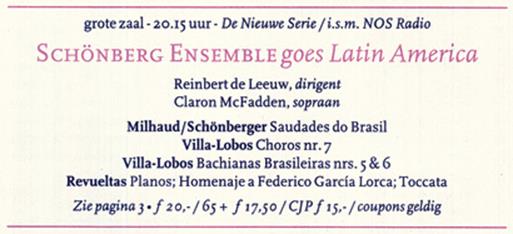
▲ 스칼라가 처음 적용된 예. 프레던뷔르흐 프로그램 인포메이션의 세부. 얀 빌럼 덴 하르토흐 디자인, 1989년
스칼라의 형태원칙은 벰보(Bembo) 등 인본주의적 활자체와 18세기 중반 프랑스의 타이포그래퍼 피에르 시몽 푸르니에의 활자체들로부터 결정적인 영향을 받았다. 다만, 나는 대개의 포스트스크립트 폰트들이 너무 가늘다는 걸 몸소 느낀 바 있어, 스칼라에서 획의 굵기는 고르도록, 세리프는 단단하도록 만들었다. 이탤릭체는 아리기(Arrighi) 등 16세기 이탈리아 명필가들의 필체에 어느 정도 근거를 두었다. 단, 스칼라의 이탤릭체는 상당한 수준의 세부까지 그 정체와 밀접히 연관되어 있다.1) 스칼라 전체 패밀리를 디자인하는 과정 동안 내게 한 가지만은 분명했다. 소문자형 숫자가 별도로 분리된 올드 스타일 피겨(osf) 폰트 아닌 일반(normal) 폰트에 포함되기를 원했다는 점이다. 일반 폰트에는 대문자형 숫자(table figure 2))들만 들어가는 다소 비논리적인 관습에 반하는 일이었다.
역주 1) 16세기 이탈리아 명필가들인 아리기, 타글리엔테, 팔라티노 등의 흘림체는 이탤릭체의 직접적 모태가 되었다. 그들의 흘림체는 아직 정체와 쌍을 이루지 않은 독립적인 필체였다는 점에서 오늘날 이탤릭체와 개념이 다르다.
역주 2) 국내에서 전문 타이포그래퍼들 아닌 일반에게는 이 숫자 형태만 익숙할 것이다. 소문자형 숫자는 어센더, 디센더가 있어 4선을 기준으로 하지만, 대문자형 숫자는 대문자처럼 위아래 2선을 기준으로 배열되므로, 위아래 높낮이가 일정하여 한글과는 성격이 더 잘 어울리기도 하다. 위아래 두 줄이 쳐진 표(table)의 한 칸 안에 배치할 때 한 눈에 알아보기 효율적인 숫자라서 table figure라고 한다. 19세기에 등장해서 널리 퍼졌으므로, 소문자형 숫자들은 그에 대비하여 올드 스타일로 구분하기도 했다.
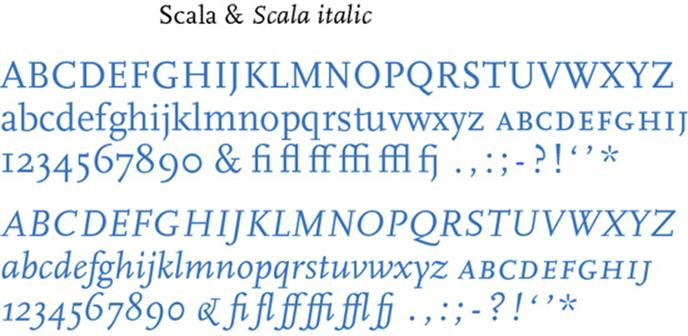
▲ 스칼라와 스칼라 이탤릭체 개괄
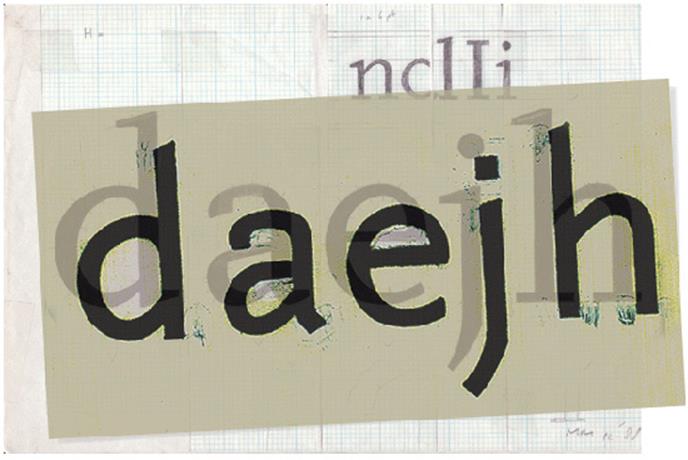
▲ 세리프를 가진 스칼라를 스칼라 산스로 바꾸는 방법
스칼라 산스는 말 그대로 스칼라로부터 파생되었다. 나는 검정 마커과 수정액을 사용해 세리프 글자들을 산세리프체로 바꾸었다. 그 결과 스칼라 산스는 보다 ‘인본주의적’ 글자체의 외관을 가지게 되었다. 당시까지만 해도 이런 면모를 가진 산세리프체는 드물었다. 주목할만한 몇몇 예외가 있다면 런던 언더그라운드(London Underground), 길 산스, 로물루스 산스, 신택스(Syntax, 한스 에두아르트 마이어 디자인) 정도였다. 신택스 정체는 이제껏 존재했던 그 어떤 산세리프체와 비교해도 진실로 아름답지만, 안타깝게도 그에 수반한 이탤릭체는 기울어진 정체였다. 이탤릭체의 산스가 어떤 형태를 가져야 하는가에 관해 일반적으로 통용되던 견해들로부터 스스로 자유로워지기엔 마이어에게 때가 아마도 너무 일렀던 것 같다.
◀ 신택스 정체와 이탤릭체
산세리프체를 위한 소문자형 숫자들을 디자인하고 나서야, 나는 그 시기까지 소문자형 숫자들이 산세리프 활자체에는 보이지 않았더란 사실을 발견했다. 에릭 길조차도 길 산스에 이들을 만들어 넣은 적이 없었다. (모노타이프사가 이들을 추가해넣은 건 1990년대의 일이었다.) 기묘하게도 오히려, 렌너가 유일하게 이들을 푸투라에 디자인해서 넣었다. 비록 좀처럼 사용되는 일은 없었지만 말이다.
▲ 푸투라와 길 산스의 소문자형 숫자들
스칼라 산스 이탤릭체는 그 정체가 가진 모든 대응물의 형태를 그야말로 등가적으로 따른다. 이탤릭체는 작은 대문자, 이음글자와 소문자형 숫자를 포함한다. 이로써 스칼라는 세리프체와 산세리프체, 정체와 이탤릭체 모두에서 이 모든 부호들을 갖춘 첫 패밀리가 되었다.
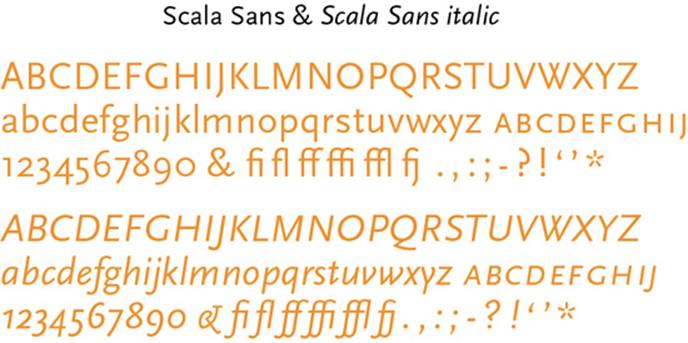
▲ 스칼라 산스와 스칼라 산스 이탤릭체 개괄
스칼라와 스칼라 산스를 디자인할 때 나의 모토는 ‘두 개의 활자체, 하나의 형태원칙’이었다. 스칼라와 스칼라 산스 각각의 정체와 이탤릭체가 가진 공통된 골격을 따로 떼어놓고 보면 이는 분명해진다.
▲ 스칼라(파란색)와 스칼라 산스(주황색) 활자체의 정체와 이탤릭체 버전의 골격들
세리프체와 산세리프체에 관한 이런 생각들을 실행할 때 새로운 디지털 디자인 기술의 가능성들에 힘입어 나는 굉장한 자유를 누렸다. 내가 타입페이스 회사에서 일하는 것도 아니었으니, 시간적 압박도 없었고 음악센터는 나를 전적으로 믿어주었다. 이런 환경에서 나는 세리프와 산스에 관한 생각을 아주 자유롭게 펼칠 수 있었다. 상당수의 일반적 통념들은 내게 논리적으로 여겨지지 않았다. 그들을 따르지 않아도 되었으니 독자적인 디자이너로서 나는 운이 좋았다.
1990년, 스칼라는 폰트샵 인터내셔널의 진지한 첫 본문용 활자체로서 출시되었다. 하지만 이 패밀리가 극도의 명성을 누린 건 3년 후 스칼라 산스가 부각되면서부터였다. 세리프와 산스를 하나로 묶은 활자체는 전 세계 그래픽 디자이너들이 쓰기에 매우 유용하다는 사실이 드러났다. 1997년, 나는 스칼라에 라이트, 블랙 등의 웨이트와 컨덴스드(condensed)를 추가했다. 스칼라 주얼(Scala Jewels)이라 불리는 네 가지 디스플레이용 버전들도 디자인했다.
텔레폰트. 그 와중에 만들어진 단독 산세리프체
1993에서 1994년 사이, 나는 네덜란드 전화번호부를 위한 텔레폰트 리스트(Telefont List) 와 텔레폰트 텍스트(Telefont Text)를 디자인했다. 내가 의도한 활자체는 산세리프체로, 이번에는 산세리프의 근간으로 쓸 특정 세리프 활자체를 염두에 두지 않았다. 나는 스칼라 패밀리를 디자인하는 동안 얻은 경험을 활용할 수 있었지만, 스칼라 산스 작업과 비교했을 때 제약조건들을 훨씬 많이 고려해야 했다. 둘 중 먼저 디자인했던 텔레폰트 리스트는 면적을 가급적 덜 차지하도록 값싼 종이에 작은 크기로 인쇄하면서도, PPT(Post, Telefonie, Telegra¬fie)가 이전에 사용해온 닳아빠진 유니버스보다 훨씬 읽기 편해야 했다. 동시진행적으로 나는 전화번호부 자체의 새로운 타이포그래피 디자인을 고민했다. 이렇게 할 수 있었던 것은 대단한 이점으로 드러났으니, 나는 내가 4단 그리드 안에서 수정한 결과로서의 활자체를 세부까지 미세하게 조정할 수 있었던 데다, 그렇게 활자체를 수정하고 나서는 다시 페이지 레이아웃을 조율할 수도 있었다. 이는 활자 디자이너로서 드물지만 이상적인 상황이었다. 어떤 경우든 서적 디자이너로서의 경험은 유용하게 작용했다.
▲ 텔레폰트 리스트와 텔레폰트 텍스트 개괄
텔레폰트 리스트는 자동적으로 생성되는 전화번호부 목록에 쓰기 위한 정말 활용도 높은 활자체인 반면, 텔레폰트 텍스트는 작은 대문자나 소문자형 숫자들처럼 타이포그래피적인 세부를 다듬기 위한 숱한 장치들을 써서 일일이 고르게 조율해야 하는 안내 페이지 등의 지면을 위해 디자인한 활자체였다. 이에 대해 나는 이렇게 요약하곤 한다. ‘많이 사용하는 활자체일 수록 기능의 폭이 좁고, 별로 사용하지 않는 활자체일수록 기능의 폭이 넓다.’
텔레폰트 리스트와 텔레폰트 텍스트는 1994년 이래 네덜란드 전화번호부에만 독점 적용되어 왔지만, 근자에 출시될 가능성도 없는 것은 아니다. 그럼에도 내게 텔레폰트 세리프를 만들 계획은 없다. 산세리프체로부터 세리프체 디자인을 파생시킬 수는 없는 노릇이다.
세리아와 세리아 산스, 문학작품을 위한 활자체
1996년 여름, 베를린에서 바르샤바로 돌아가는 기차의 식당칸에서 가져온 식탁용 냅킨 위에 나는 세리아(Seria)의 첫 스케치를 끄적거렸다. 스칼라가 문학작품 텍스트에는 어울리지 않더라는 불만이 세리아 디자인의 촉매가 되었다. 시나 다른 문학작품들에 쓰기에 스칼라는 어센더와 디센더가 너무 짧다는 점을 간파하면서, 나는 서적 디자이너로서 이런 텍스트에만큼은 스칼라를 사용할 수가 없었다. 어센더와 디센더를 길게 늘린 버전의 스칼라도 고려해봤지만, 다음 순간 내가 원하는 건 몇몇 디테일만 수정하는 것 이상이라는 사실을 깨달았다. 스칼라는 스칼라이니, 수정을 가하려거든 아예 긴 어센더와 디센더를 가진 새로운 활자체를 만들어야 하리라고 나는 결심했다. 이때, 좀더 경제적이거나 지면을 절약하는 활자체를 만들고자 하는 목적은 없었다.
어떤 의미에서, 지난 15년은 산세리프 활자체의 혁명기였다. 보다 많은 활자 디자이너들이 산세리프체의 기원을 자각하게 되면서, 산세리프 디자인은 세리프 디자인을 동반하기에 모자랄 것 없는 파트너가 되었다. 다가오는 15년은 아마도 슬랩세리프 활자체의 혁명기가 될 것이다. ‘넥서스 원칙’은 그 이후에도 네 가지, 다섯 가지 구성원이 중첩되며 확장되어 갈 것이다. 시간이 모든 것을 말해주리라.